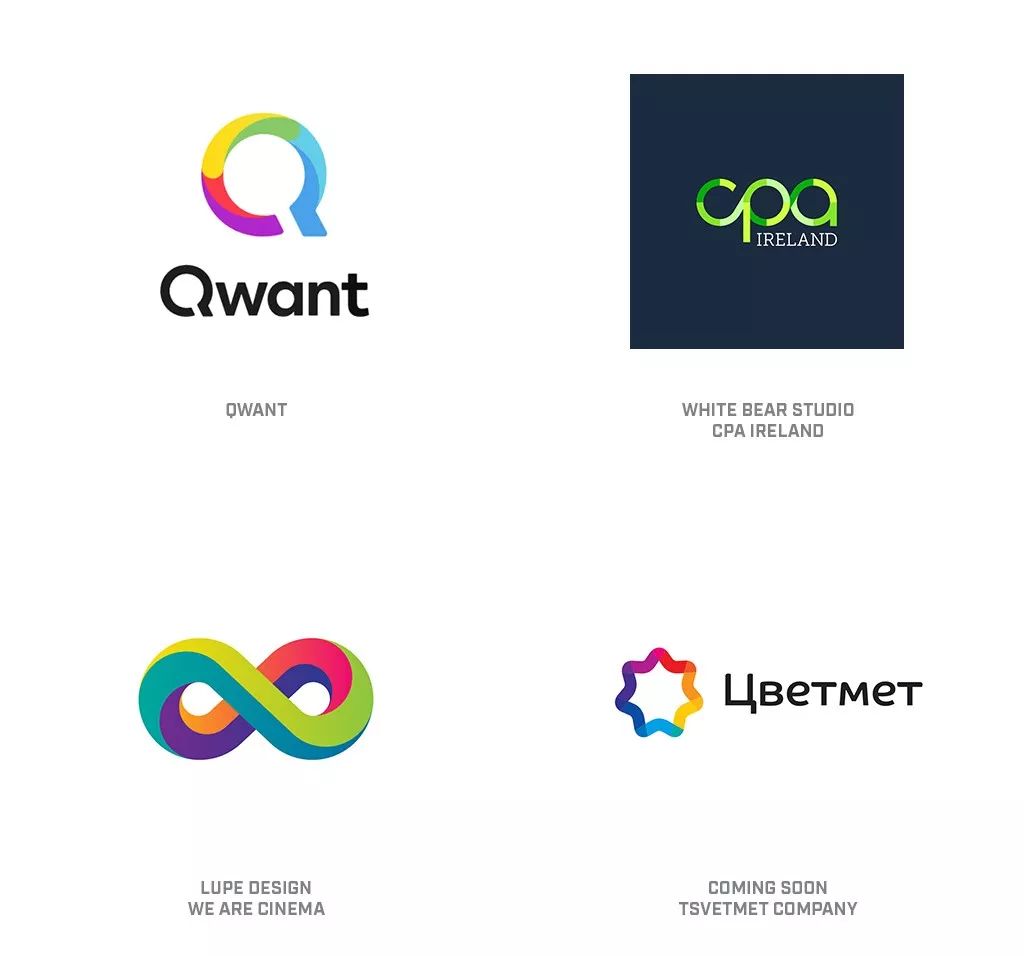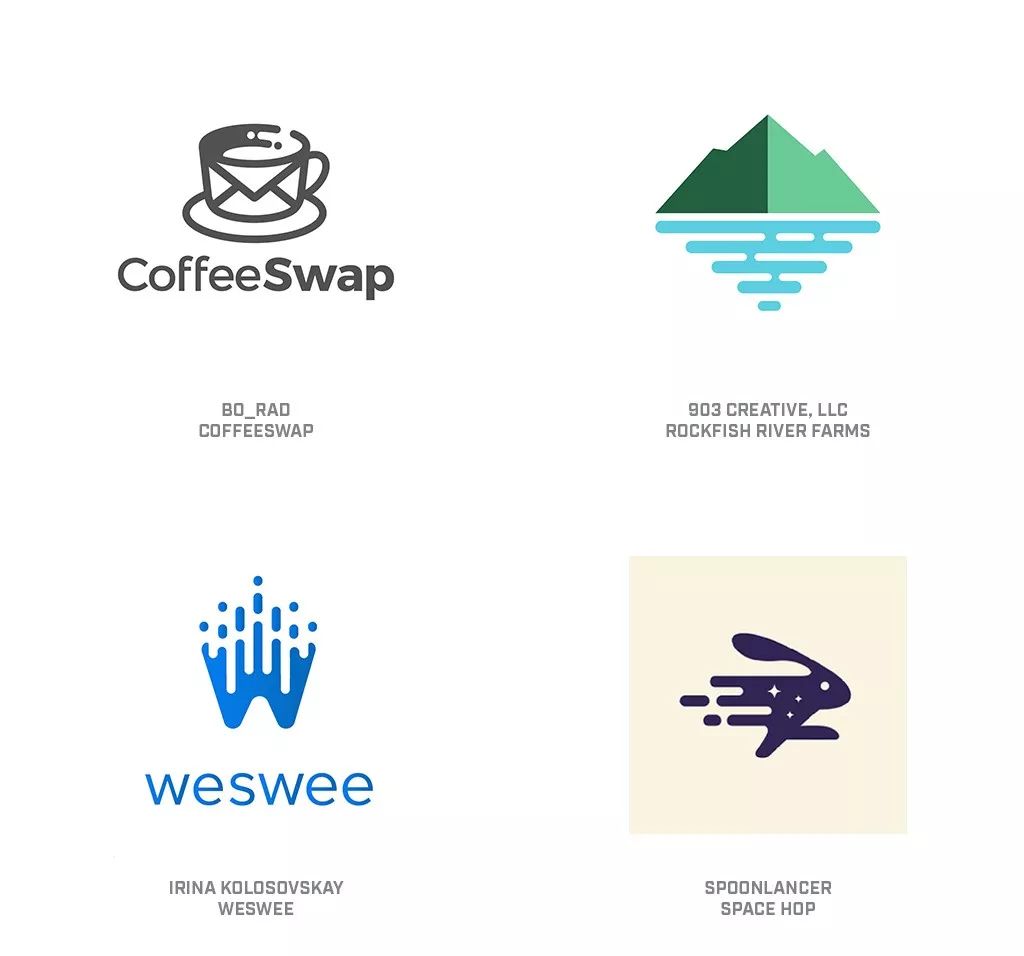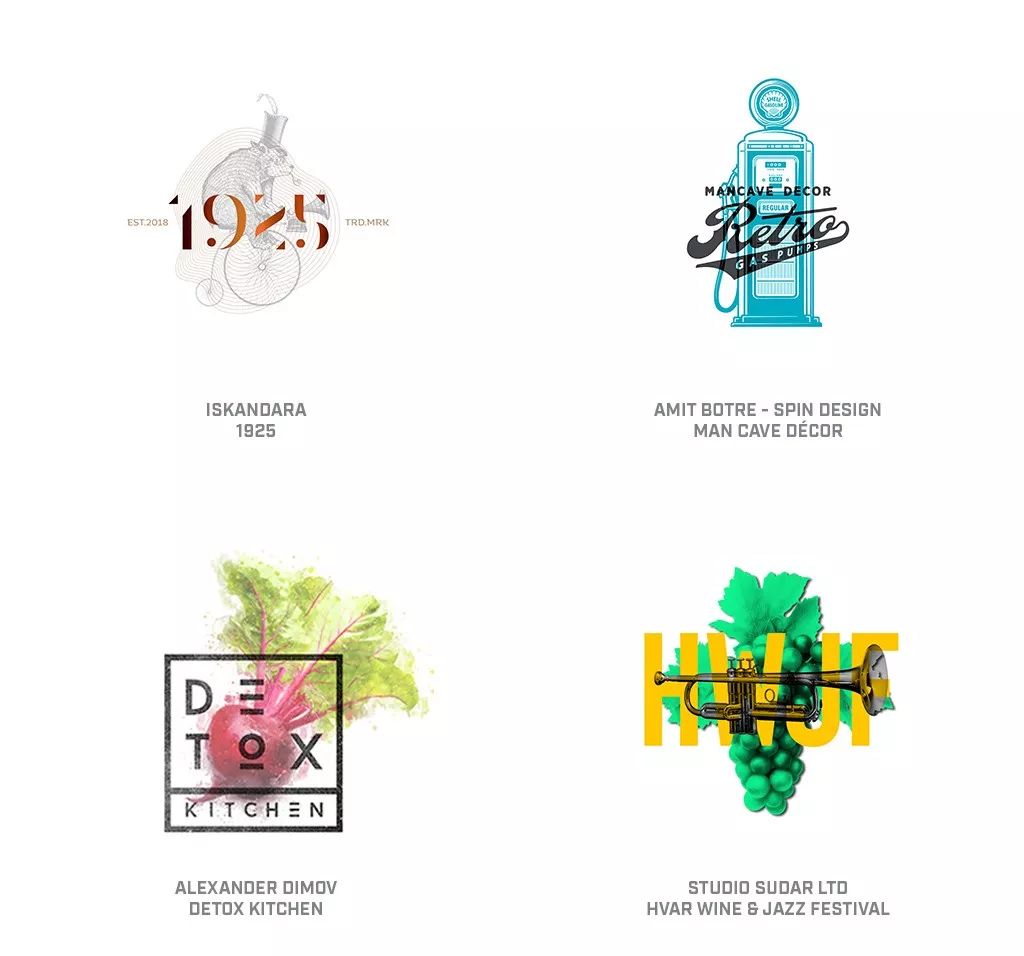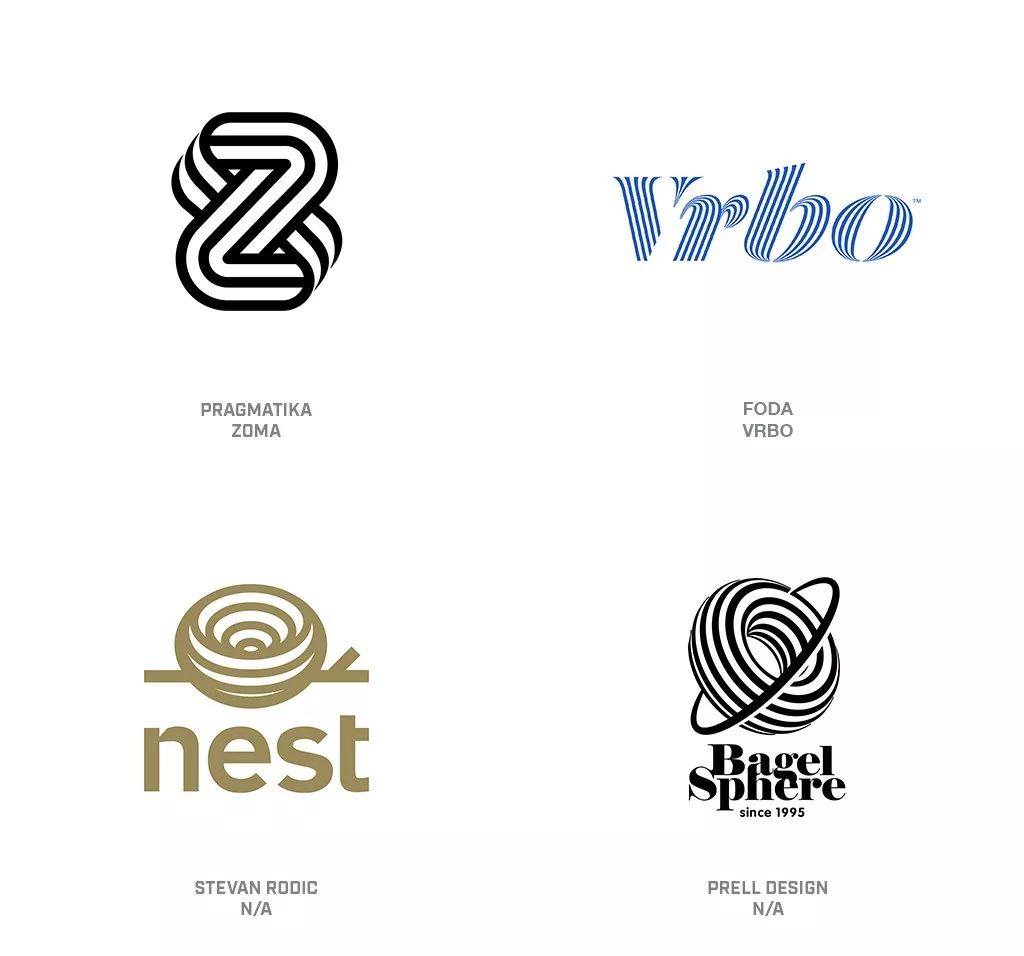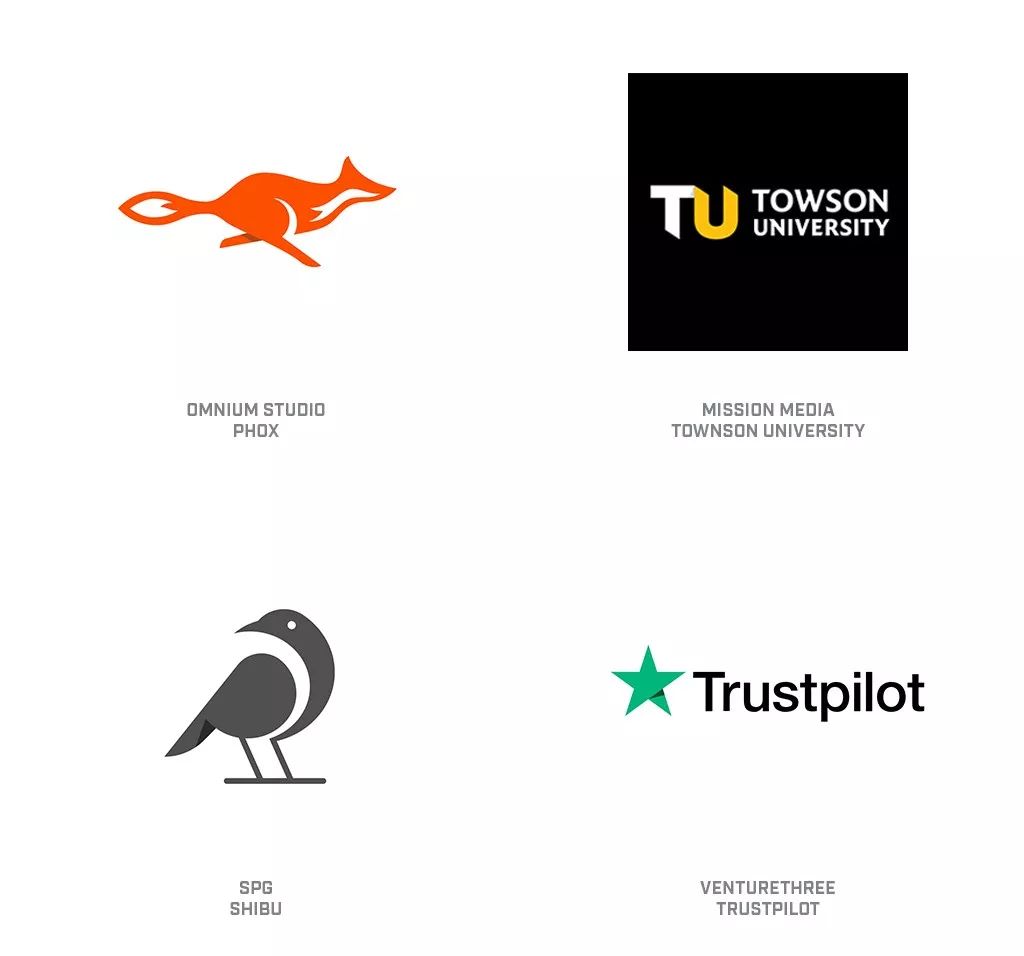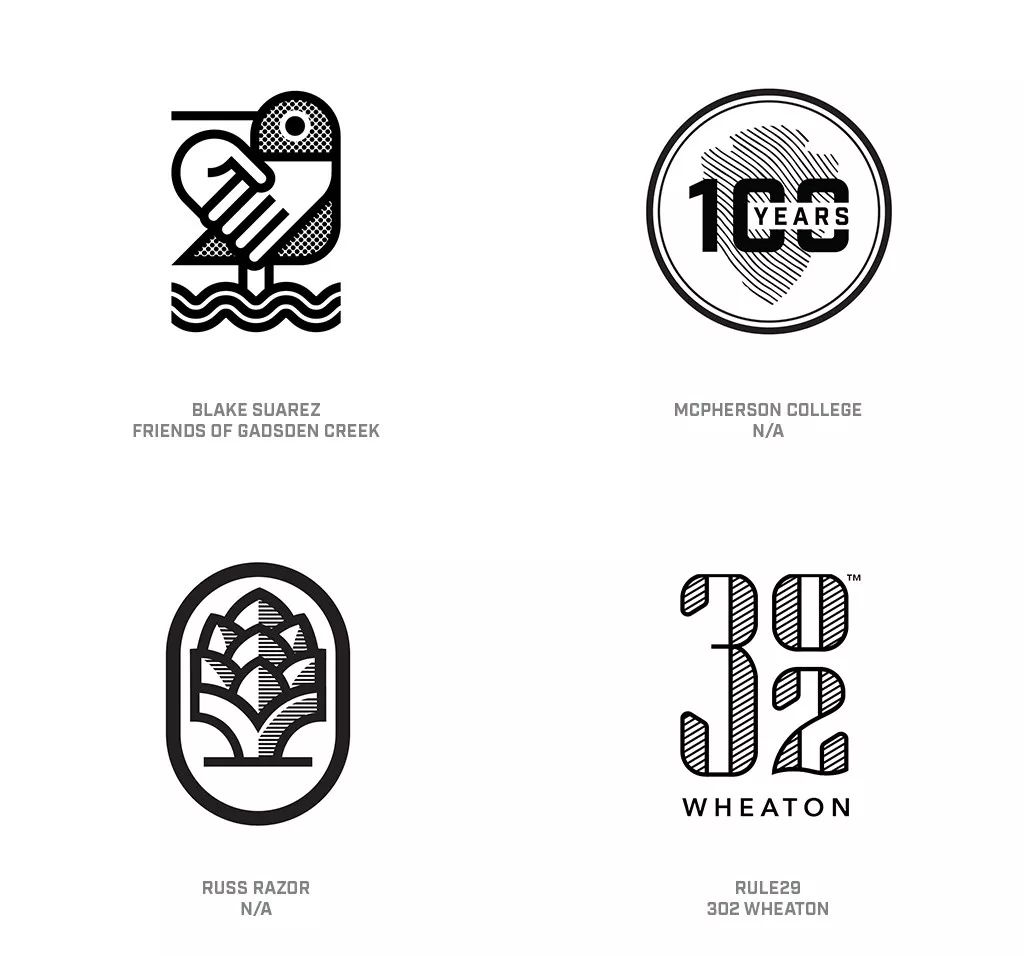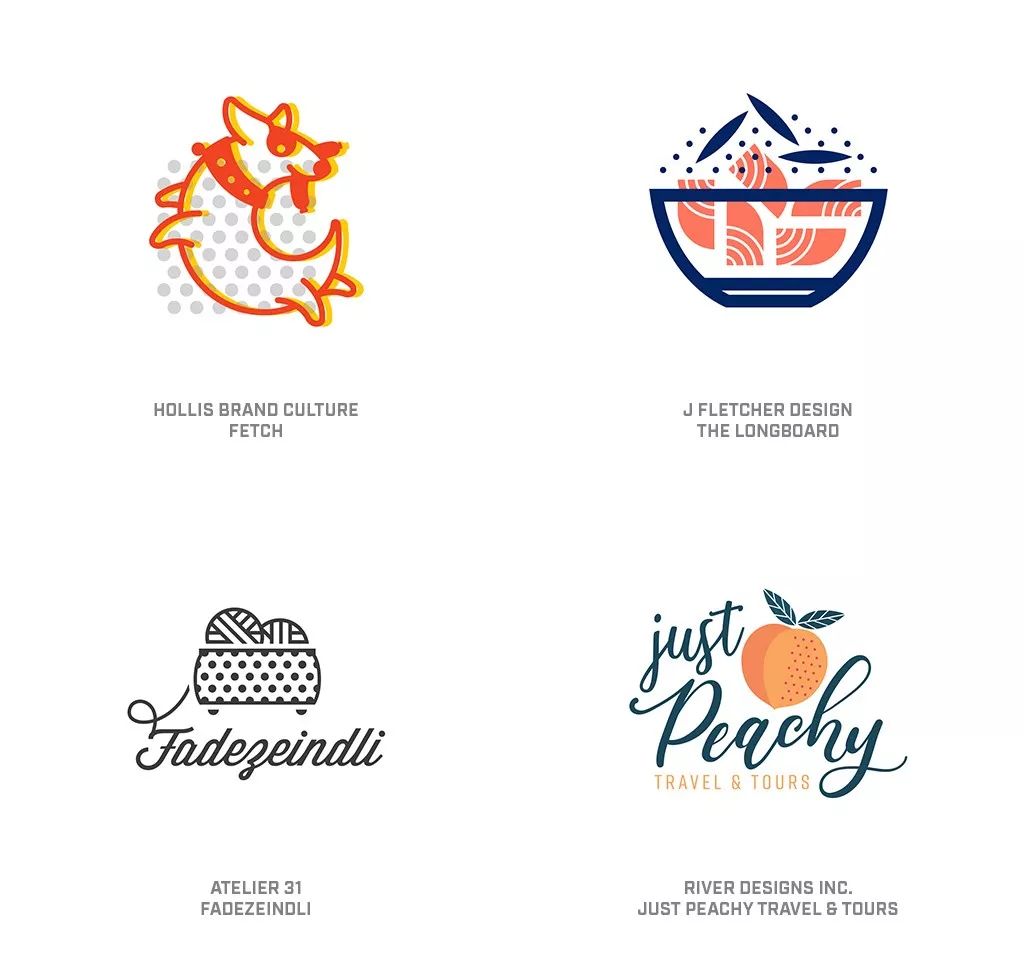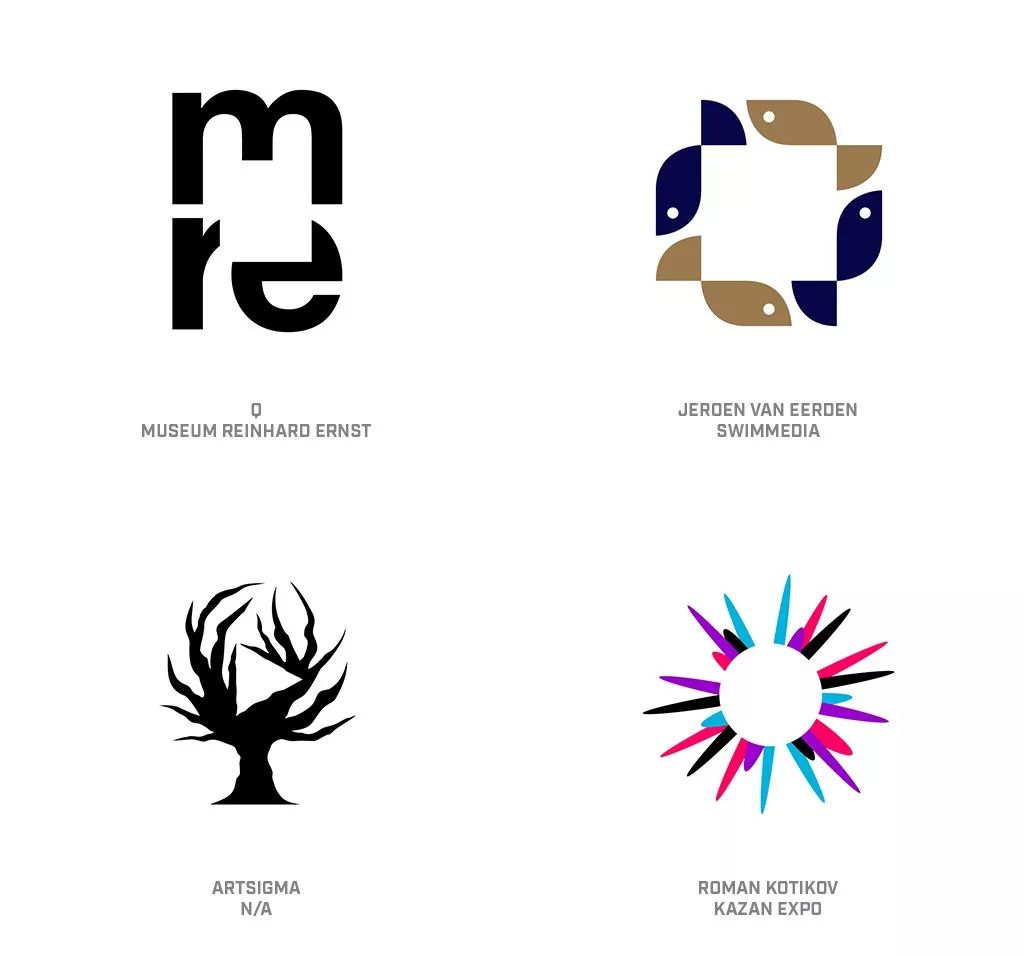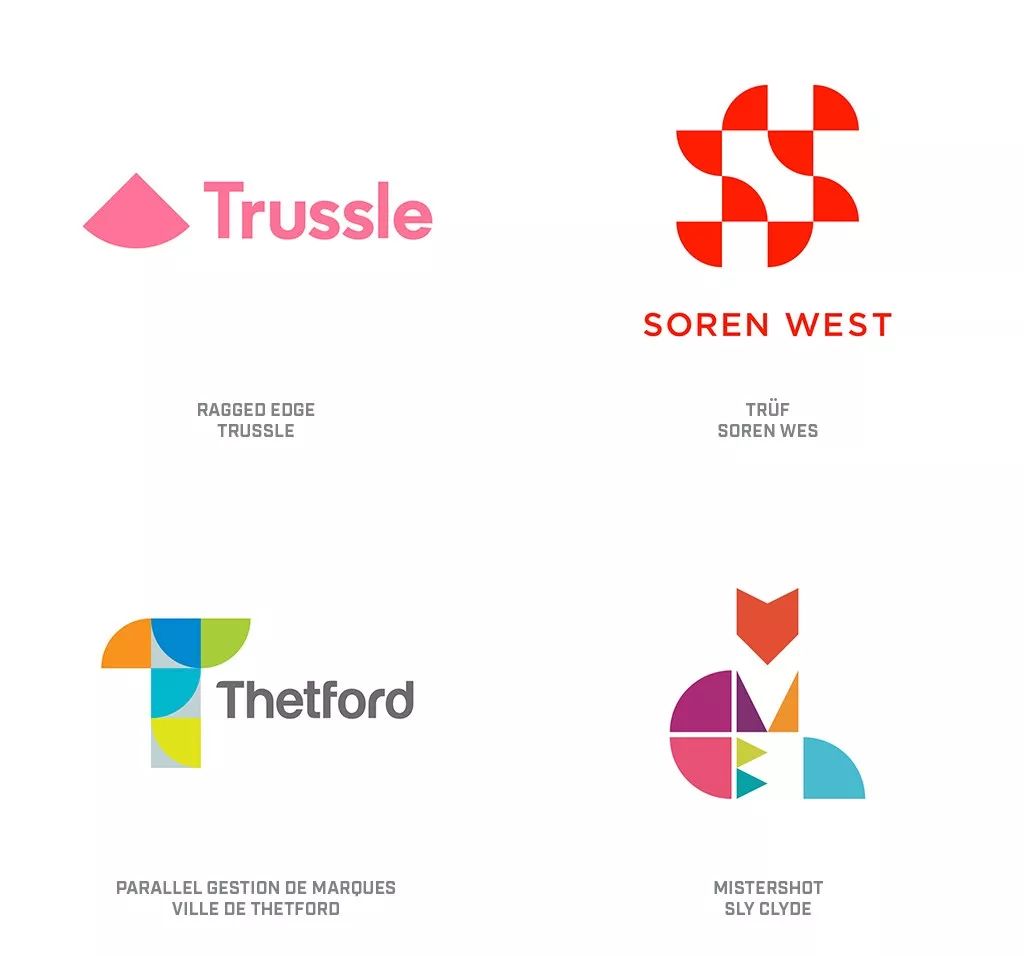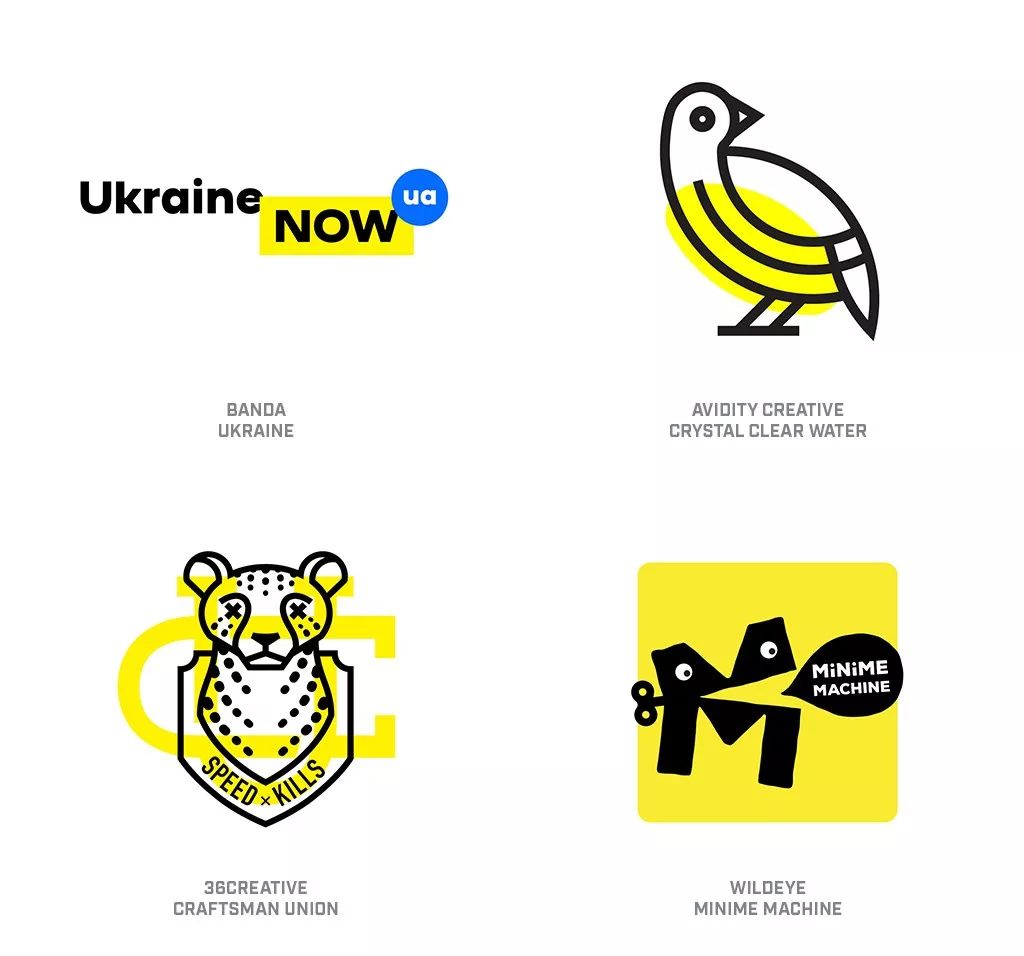
2019全球logo设计趋势报告
今年的趋势继续显示出设计师们在进行设计工作时是勤奋的、好奇的、充满求知欲的,这推动着我们达到更高的高度。你会在今年的主题中看到过去某些主题的延续,但是有着自己独特的倾向性。渐变继续以新的、具有启发性的方式发展,设计师们采用了不那么传统的颜色曲线,比如红色直线变成绿色,或者蓝色直线变成橙色。这些倾向于在互补色之间创建一个色调过渡区,但是也伴随着更多的相邻颜色的变化,比如Instagram上的橙色、品红和紫色,我们继续寻找无人认领的渐变所有权。
设计师们似乎也发掘出了大量腐朽的Zipatone或Letratone图形胶片。粗大的砂砾点、条纹和中间色调与一些木纹和俗气的砖块图案调和在一起,为原本可能充满色彩的粗大痕迹增添了装饰。这些标志似乎呈现出一种复古的单调外观,与高色度渐变趋势背道而驰。
现代文化继续改变我们解释符号的方式,以及我们如何在视觉上优先考虑语境,颠倒了视觉识别和应用之间的关系。随着纹理、图案、排版、摄影和说明性元素在视觉品牌层次中的位置发生了变化,视觉词汇得到了更大的信任。
再比如,有太多的动画轨道类型。每一种都是经过精心设计的,但依赖于与其他六种方法相同的基本效果,很难建立区别。尝试新事物从来都不是坏事,但我们仍希望以自己独特的方式与技术进步合作,真正留下自己的印记。
此外,在探索蓬勃发展的氛围中,越来越多的作品集以设计师的幻想为特色,虽然它加强了创造的自由,而且这种做法增加了设计师的能力,但我必须承认,它会让人丧失评估有偿工作真正方向的能力。
再一次,我不得不提醒大家,趋势并不是指时髦的。与时尚不同的是,真正的趋势不会随着文化变迁而沸腾,而是向两个方向延伸来与过去和未来的身份握手。我们不断地留下面包屑,这样我们就可以从过去的好作品中吸取灵感,同时还能开辟出一条永远不会与过去完全相同的未来之路。
趋势一:摩尔斯阴影  Morse Shade
今年我们的工作小组精心设计了一种新的方式,在他们的设计作品上使用阴影,但是想要避开另一个渐变颜色的领域而选择了单色调。用一连串减少的笔画来表示运动信号的想法,也已经让位于一串同心的点和破折号。我们想要用一个愉快的新方法来打破传统阴影的视觉张力,同时提供一个纯矢量解决方案。
在过去的几年里,我们看到圆点和线混合在一起,展示了不同元素的融合。通常以同心圆为中心或彼此平行运行,不合并或不从实场中出现。通过将这些元素从字段中挤出或将这些元素连接在一起,并将它们从对象中扩展出来,设计师向消费者呈现了矢量阴影,以便在他们自己的头脑中完成图像。
趋势二:复合叠加  Loaded
设计师不仅去掉了任何元素分离的伪装,还展示了图形组件的层次感,甚至在某些地方运用多个层级,以达到模糊的效果。其中大多数都传达了一种引人入胜的信息,避免了视觉元素的过载,也巧妙地吸引了人们的关注。对于大多数人来说,这种方式就是建立一个具有清晰信息的顶级高对比度图层,并将其加载到一个从属图形上。
两层就好了,三层也是可以把握的,四层就容易被破坏了。这类logo的特点是,如果背景无法辨认,最上层的信息仍将发挥作用,也类似于插图和排版的混合物。正如这些例子所示,根据你想要的主题和风格,审美可以从怀旧复古到新鲜农场。
趋势三:单一阴影  Orphan Shadows
阴影作为徽标设计中的一个常用元素,在很多方面都是至关重要的。他们可以展示自己的抱负或其他尚未确定的资产。阴影可以识别光的方向,更确切地说,它们还可以显示维度和空间关系。比如跨越一条垂直线和一条水平线,再加上一点阴影,就可以确定谁在上面了。再比如,画一匹平直色调的马,有两条腿可能会变暗一点,那一定是后腿了。
有时候,我们作为设计师会被自己的技术所困。我们罗列出来的这些徽标和最近的许多徽标都包含着一个无限小维度的影子,它们的包含似乎不合适。即使在《Trustpilot》中,它看起来确实提供了关键的分离,但我仍然想知道,如果按比例缩小,这个阴影是否还能够很好地发挥作用。这里有一个谦虚的建议,如果需要效果,确保不需要佩戴老花镜。
趋势四:拉链色调  Zip Tone
在数字时代之前,想要在插画中加入条纹、圆点、中间色调、木纹或其他异国情调的半色调,首先需要去当地的社交艺术用品商店逛逛。以Zipatone或Letratone为名的粘性背衬胶片带来了无穷无尽的效果,你可以用微不足道的钱将其应用到你的艺术中。复古设计书籍中充斥着各种各样的标志,展示着一些非常漂亮的渐变,让设计师们对这种陌生的技术感到好奇。
这一趋势所显示的徽标风格是复古的70年代,在色调的采用上也透露出复古的味道。对消费者来说,这只是下意识地回到了一个要求不那么高的时代。这是一种效果,设计师们立即把它作为一个有点粗糙但绝对是回归机器的产品。
趋势五:点  Dots
在Zip色调和高光之间的位置,就是圆点的使用。这些超大的圆点区域是一种提醒——在一个标记中放置一些粗糙的半色调屏幕,因为它们实际上代表图标的一个元素,而不仅仅是背景中的一个基础。就比如杰伊·弗莱彻(Jay Fletcher)选择他那碗食物上的点,它看起来就像撒了大量芝麻在上面。请注意,这些圆点近似于桃子的腮红,但图案并不仅仅是用来表达色调,它们可以表达一些情绪。
圆点的排布可以打破紧张的平面色调区域,使作品富有张力,并有一定趣味性,视觉上提醒我们的徽标已经精细调整。这使得设计师可以用简单而有趣的矢量重复来吸引消费者。
趋势六:高光强调  Highlights
人们很容易认为,在吸引人们注意的领域里没有什么新技巧。猿类拍打胸部,孔雀展开羽毛,人类则在社交媒体上发帖。还有一小部分视觉识别设计师会选择用高光来装饰他们的作品,或者至少这是今年最引人注目的趋势之一。
我们也发现,这些通常是黑白相间的徽标,就像是设计师们在拿给客户前用高光笔点睛地艺术品。高光的范围从不加区分到有目的的强调某些信息,运用的也都是流行的高光色调,如淡紫色、日辉光粉色和电蓝色等等。抛开其中的乐趣不谈,很多徽标的高光都是精心制作的,值得称赞的是,设计师们认识到,正是色彩的火花让这些标志摆脱了潜在的平庸。
趋势七:等分  Quarters
从过去两年开始,徽标设计的主题延续到简化设计或徽标的纯粹性。这是对前几代人作品结构和图像清晰度的致敬,这也是设计师创造性的证明,因为他们将重新排列这些几何元素,重构运用几何元素的徽标。当你听到有人说这种等分形式是以前做过的,只要提醒他们,作家和音乐家一直在重新排列了一些笔记或字母,并将它们以更适合现在时代的形式呈现。我们的创造之井并没有干涸。
今年,许多的圆圈被划分成四份,四处散布。大多数情况下,这些是唯一的构建块,但它们也与圆、半圆、正方形、三角形和其他符号或形状混合在一起。即使在表达复杂的信息时,形式的纯粹性也会继续传递出更简单、更清晰的信号。Soren West徽标当然是一个吸引人的解决方案,但距离四分之一圈的容量只有半步之遥。
趋势八:拼接符号  Spell Signs
坦白说,这些徽标给我的第一印象让我怀疑是不是有些设计师迷恋上了JK罗琳、魔法石、魔杖和斗篷,或者化身自死亡圣器。如果这些标志护身符有一个强有力的故事,他们将衷心为他们的主人服务。这样的徽标会让人们感到每一个笔画都与其他的笔画和谐一致,并且很可能充满了强大的意义。
认真又清晰的笔触、完美的角度和精准的弧度与精确的十字线相交,这些让使用者有一种一种技术上的优势,也让我们感到无懈可击。当然,应用这些标记的需要同样严格的环境,几乎没有奇思妙想的余地。如果有的话,这些符号可能正式到,足以让你穿着刚浆洗过的衬衫走进他们的办公室。
趋势九:孔洞  Holes
想象一下,在风化的公寓墙上有一个空白,这代表着犯罪现场的证据已经被移除了。不是挂在那里的东西告诉了我们什么,而是没有挂在那里的东西提醒了我们一个重要的信息。不管这个洞或形状是随意地从其他图形元素的内部雕刻而成,还是巧妙地切除不留痕迹,每一个都有同样的目的。它们作为画布存在,消费者将在上面完成整个故事。
这不仅仅是一个隐藏的负空间,就像联邦快递(FedEx)标识上的箭头,或是三角巧克力(Toblerone)山腰上的熊。这些空白字段不是为了隐藏,而是为了向消费者说明只有它们才能解决的不完整性,也让公众参与到这个品牌难题中来。
趋势十:圆点拖动  Spot Drag
你有没有过这样的体验,在你拿起笔之前,或者如果你犹豫不决停顿了一下,记号笔的笔尖突然变得慷慨起来,流出一滩可能淹没你的墨水。我知道这不是电脑的工作方式,但它确实帮助我描绘出这种趋势的视觉外观。我把笔尖画成一个完美的圆圈,在笔尖后面留下一条不变的标记线,然后在笔触结束时把整个圆圈停在那里,就像一条意想不到地在死胡同里结束的街道。
不管这些标志是褪色的、渐变的,还是清晰的、不变的,它们都传达了类似的信息。圆圈是信使,直到几秒钟前,这个标记还不存在。一个动作使这些点开始运动,它们以精确的精确度生动地在这个领域中行动,拼出一个字母、走出一条路径,或者勾画出一个有意义的符号。你捕捉到了它们的行动市,它们可能已经完成了,也可能只是在等着你转移视线,好让它们重复或继续。他们充满活力、生动、新鲜、充满潜力。
趋势十一:渐变  Gradient Breaks
在标识设计中广泛使用渐变颜色,是我们行业在过去十年中经历的最两极分化的趋势之一。现在仍然有一些设计师讨厌过渡颜色的使用,因为它违背了许多标识设计的早期规则,这些规则是在数字时代之前形成的。渐变趋势的再次兴起让我想知道,是反对者也开始引领这一趋势了,还是那些长期以来一直在使用渐变技术的人在试图通过后退几步来推动这一趋势的发展。
想象用一条充满过渡颜色的线来演示运动和变换,使用某个颜色,然后用连续的相关色调来分割它,基本上是一种阶梯式的暗色调效果。Qwant标识通过轮廓化的颜色分割来实现这一点,它真实地模拟了渐变,效果比CPA好,CPA显示了沿着路径的四等分几何分割的颜色转换。
趋势十二:轮廓条纹  Contour Stripes
条纹仍在潜在的流行趋势的竞争中占据主导地位,但在这种审美中已经有了如此多的徽标,所以发现这种趋势的发展方向变得更加困难。不过,我们终于看到一个有凝聚力的群体,把条纹带入一个扭曲的维度。仍然是大大胆的致敬国旗类型的条纹,以及三维包装,以展示从百吉饼到鸟巢的各种空间轮廓。
虽然这可能与单线设计有关,但条纹设计的走向也将这个概念推向了另一个层次。用可变的条纹笔画去表现一些维度的变化,依赖于消费者去完成解释,他们仍然看到一个有序的节奏,展示了技术的准确性,测量的方法、能力和一致性。将这些属性附加到客户机的符号实施例上,您就找到了一个智能解决方案的可能核心。
趋势十三:句点  Period
去年的报告讨论了在设计中巧妙的使用与单词符号相关的标点符号的趋势,正如标题所示,句号在所有的符号中占了上风(使用最多)。在句子末尾出现只是这种符号的最基本使用方法,这种标记还可以作为符号的封顶,也可以串成椭圆,它可以作为一个领域的开始,也可以作为一个对话的结束。
也有可能句点只不过是一个点,漂浮在文本周围。在可见的标记中,这些句点实际上是丢失的字母i的残迹。比如visible,两个圆点就代表了单词中的两个i。正是设计师将一个词或一个字母的意义从传统语境中剥离出来,从而提升了设计对话的智慧和趣味。
趋势十四:翅膀  Wings
设计师们通常喜欢将飞行的本质归结为一组羽毛翅膀带来的流畅美感,进一步剥离其本质,也使空气动力学可以在灵动的设计中展现。尽管这些翅膀没有任何飞行的痕迹,但我喜欢它们本来的样子,我知道它们是翅膀。以空气动力学的姿态向前倾、或向后掠,对抗大风带来的变幻莫测的形态,这些形态都是接近现实的。
如果用字母来表现飞行或翅膀,它应该是一个字母U,一条短腿倾斜在一边,向前或向后倾斜到最佳的倾斜位置。从这个角度进行设计,以加强徽标的流线型。这种类型的徽标已经有了足够多的迭代,但许多似乎都引用了一个字母,比如Jetta的J或DoorDash的D。大量的Fs、Ps和非字母一起孕育了这对双翼。苹果有翅膀,乌龟也有翅膀,用翅膀填补空白,我们很可能会找到它。
趋势十五:门  Doors
在视觉上使用通往另一个世界、时间维度或至少另一种心境的门,已经成为今年的一种趋势。门和窗让我们能够窥视到另一个维度,同时门和窗也是真实存在于我们现实生活中的物件,它们的目的是邀请我们成为一个窥探者或参与者。
门象征着通行的权利、通往解决方案的途径、机会或欢迎的标志。窗户在很大程度上被认为是一组眼睛,让你看到别人的灵魂或另一个世界,它们是这里和那里之间的连接点。这些例子在字面上是相对的,但是对段落的引用在隐喻表达中也同样有效。